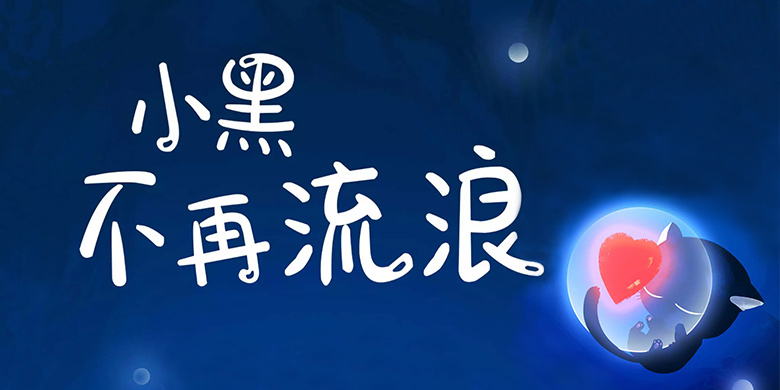
品牌:方正手迹设计师:余丹发行时间:2019字库编码:大陆简体(GB2312-80)分类:创意书写字体属性:精品字
这款字体,在每个字上都加上了白色的圆点,类似于高光的效果。整体字形圆润饱满,用笔简洁,有满满的可爱小女生的气息。适用于少年儿童类的书刊、品牌广告和产品包装设计,以及社交网络的个性化用字。
品牌:方正手迹设计师:余丹发行时间:2019字库编码:大陆简体(GB2312-80)分类:创意书写字体属性:精品字
这款字体,在每个字上都加上了白色的圆点,类似于高光的效果。整体字形圆润饱满,用笔简洁,有满满的可爱小女生的气息。适用于少年儿童类的书刊、品牌广告和产品包装设计,以及社交网络的个性化用字。